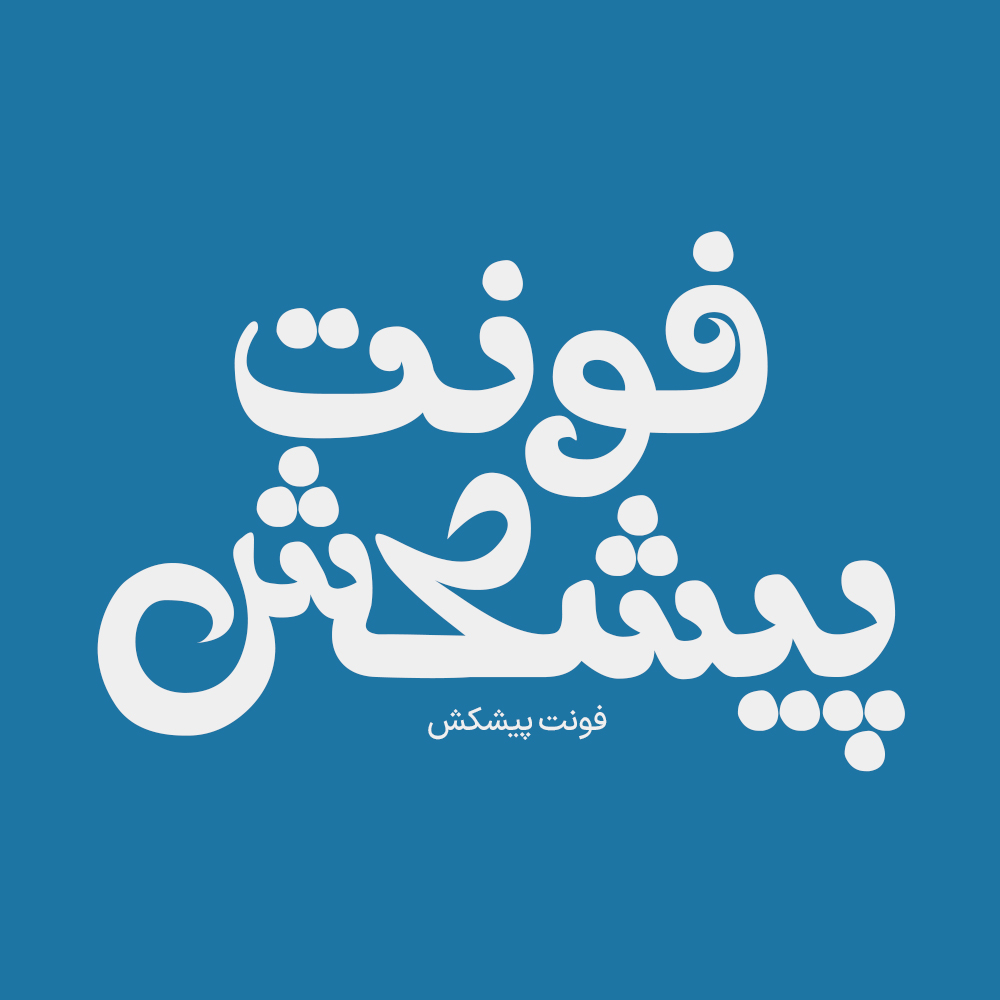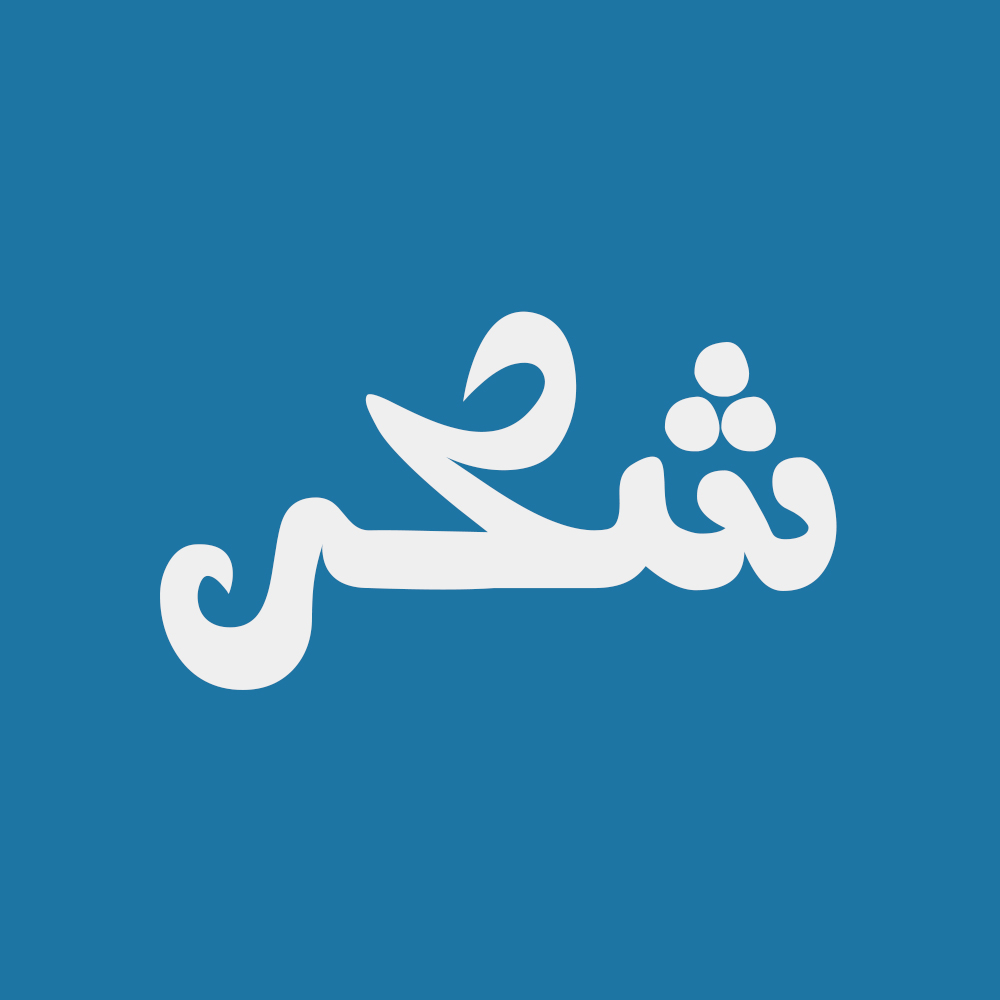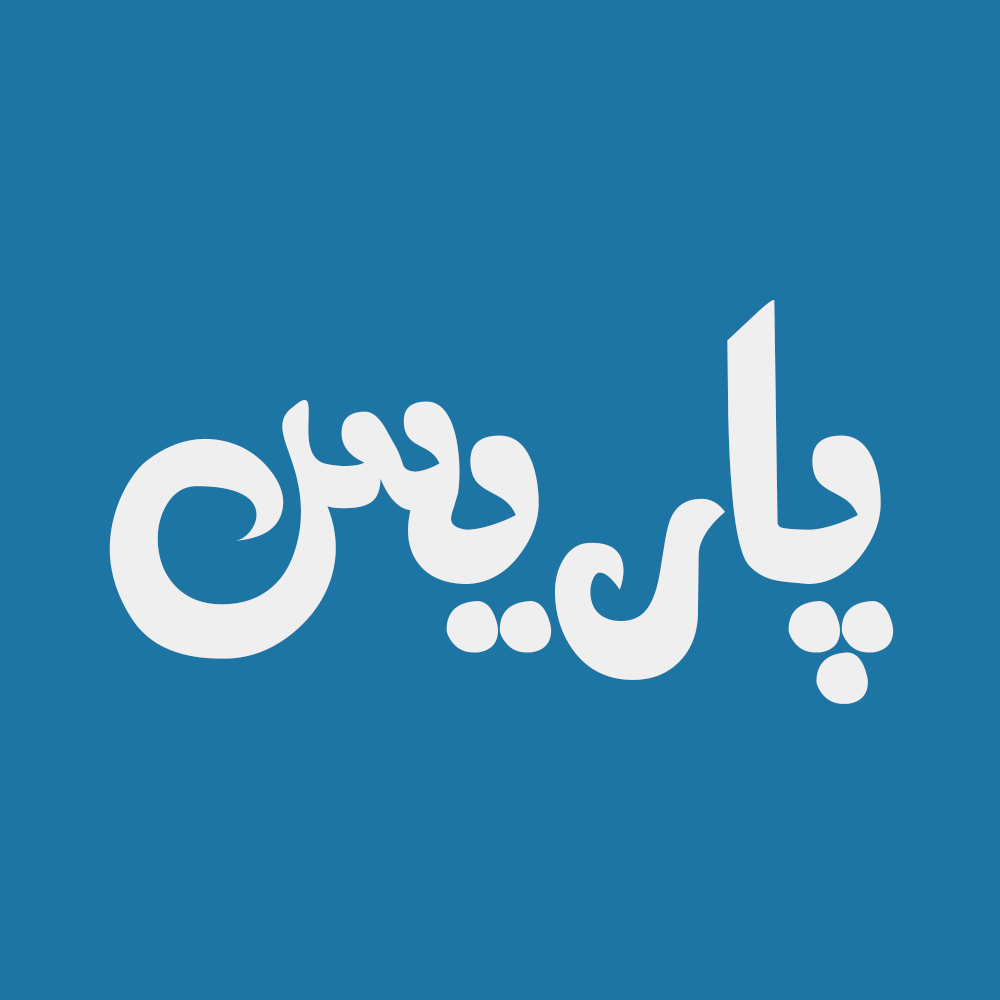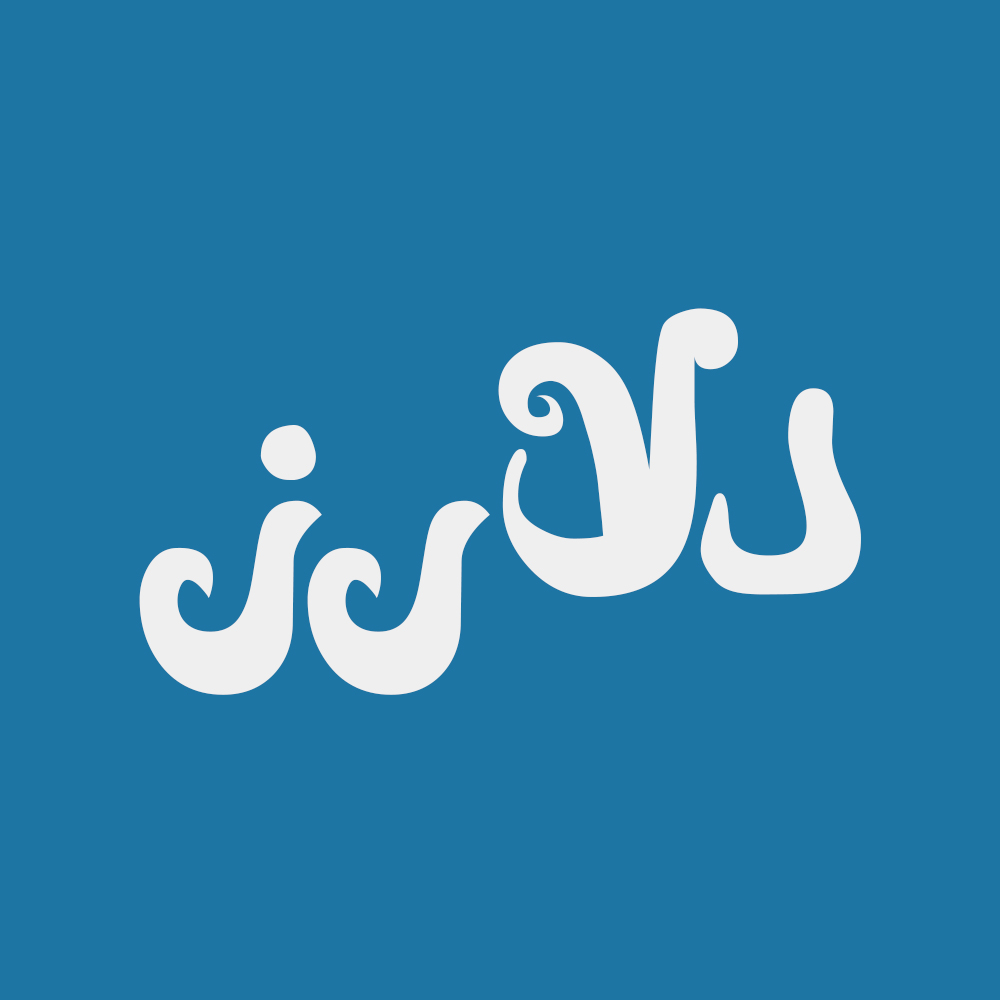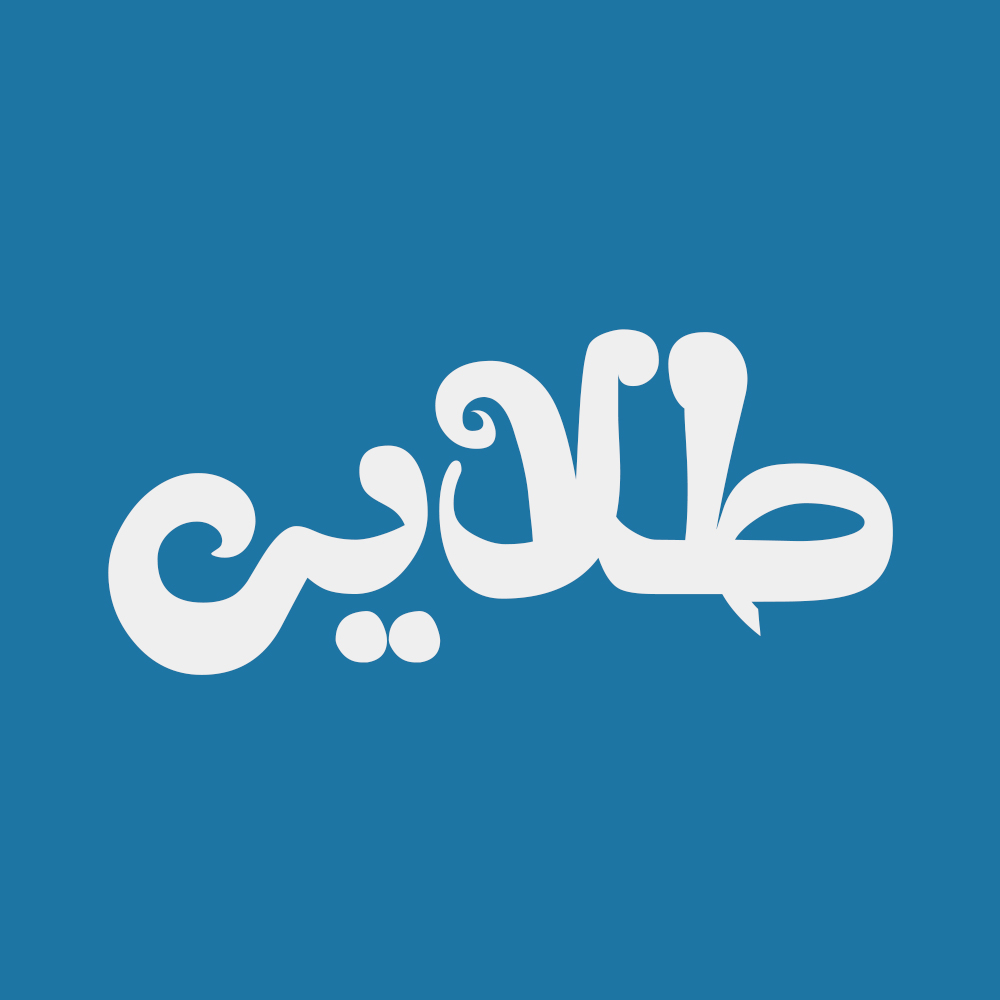
فونت فارسی پیشکش Pishkesh Font
فونت فارسی پیشکش تایپ فیسی که تلاشی وافر در جهت انسجام در کلمات به کمک تنظیم دقیق فاصلهی حروف بوده انجام گردیده است. فونت لوگو پیشکش قلمی معتدل، منظم و واضح است که انتخابی بسیار مناسب در متون ادبی و مطبوعاتی، عنوان، طراحی لوگوتایپ، طراحی تایپوگرافی و… می باشد.
خوانایی بالای فونت پیشکش به سبب رعایت جزئیات و زوایای داخلی و خارجی سطوح فونت لوگو فارسی در نوع خود بی نظیر می باشد. این فونت با فرمهای سخت و نرم خود مناسب استفاده در لوگوهای نوشتاری می باشد. همچنین از این فونت در طراحی تابلوهای چلنیوم هم به دلیل ساختار منحصر به فردش می توانید استفاده کنید. در ادامه برای شما نمونه تایپ های این محصول حرفه ای رو آماده کردیم که میتونید مشاهده کنید.
پیشنمایش و نمونه تایپ های فونت پیشکش